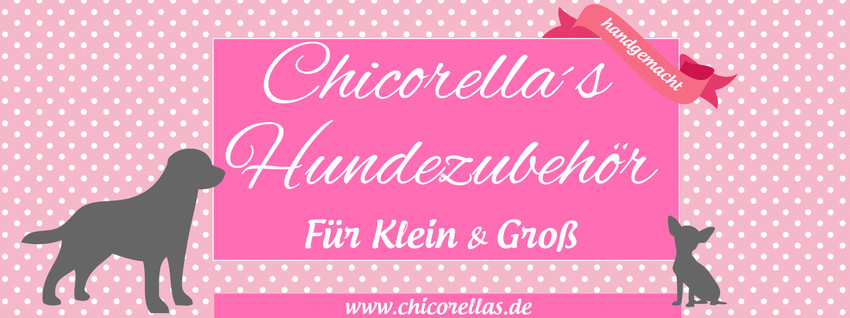
Liebe Community - wer kennt die Schrift?
Liebe Community, meine Frage, welche Schrift ist die unter "Chicorellas Hundezubehör"? Die obere ist Alex Brush. Aber die untere? (Für Klein & Groß und www.chicorellas.de) Bitte helft mir. :)
Eine unmögliche Schriftmischung. Es ist besser, nicht rauszubekommen, welches die zweite Schreibschrift ist und stattdessen ne gescheite Schrift, beispielsweise irgendeine Serifenlose, zu nehmen.
Ich hätte auch nicht unbedingt die verschiedenen Rot-Töne miteinander kombiniert.
Die sind aber »handgemacht«, da sieht jedes Rot einfach etwas anders aus.
Nee, nee, Jungs. Das ist schon so zielgruppengerecht. Deshalb sag ich auch nichts zum Apostroph. :tuschel: